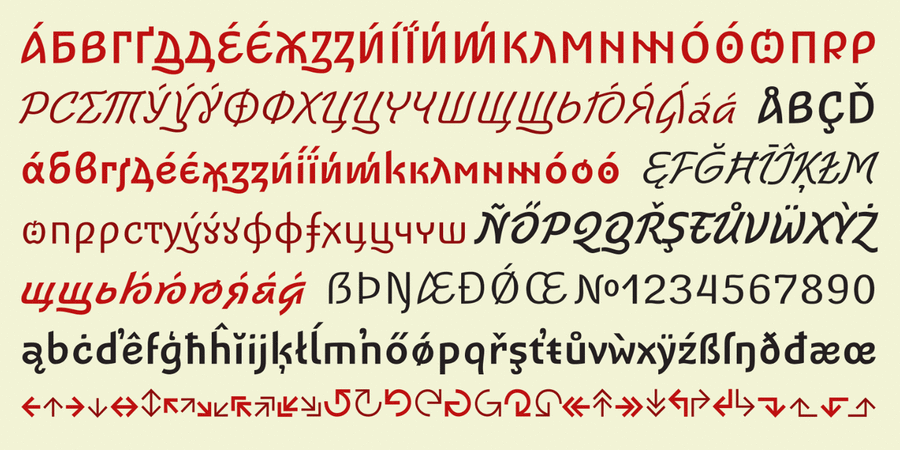
Гарнітура Ruthenia Sans є втіленням ідей відомого українського каліграфа Василя Чебаника для відновлення індивідуальних рис української абетки та позбавлення її від примусової московізації та наближення до петровського «гражданського шрифту». Це сучасний український гротеск з присмаком каліграфії для широкого спектру задач. Містить також більш історичні альтернативи, дроби та старостильні цифри, кириличну альфанумеричну систему, декоративні рослинні мотиви та широкий спектр стрілок. Рутенія Санс може працювати гротесковою парою до ґарнітури Рутенія (Rutenia), створюючи таким чином шрифтову систему. Шрифт розробив Віктор Харик у 2019-2022 році.
Асоціації з сімейством шрифтів Ruthenia SansОсобистість і характер гарнітури:
приємний, доброзичливий, ввічливий, акуратний, органічний, довірчий, оригінальний, самобутній, цікавий, пластичний, гнучкий, гладенький, якісний, динамічний, живий, чесний, здоровий, позитивний, теплий, сміливий, характерний, вільний, етнічний, натуральний, традиційний, вольний, колоритний, артистичний, художній, природний, героїчний, темпераментний, активний, племінний, рукотворний, зелений, виразний, вигнутий, привітний, ритмічний, швидкий, рослинний, творчий, поетичний, впевнений, стійкий, переконливий, мотивуючий
історія, культура, музей, література, театр, реконструкція, фольклор, музика, тату, татуювання, сувенір, геральдика, пам'ятник, меморіал, танець, прикраса, мистецтво, Трофей, нагорода, вишиванка, етнографія, банкнота, монета, туризм, природа, графіка, ілюстрація, пейзаж, козак, поезія, алкоголь, закуска, спеції, пиво, таверна, паб, кіно, горілка, замок, прапор Гарнітура має ознаки стилів: